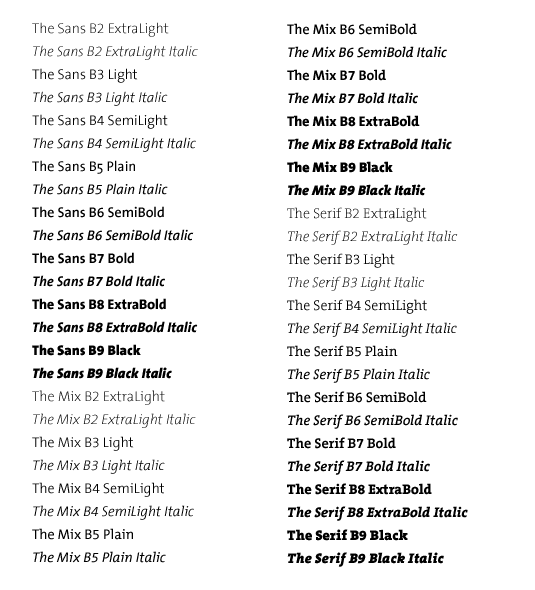
Unterschied Condensed und Narrow
gibt es eigentlich einen allgemeinen Unterschied zwischen Narrow und Condensed, oder nur bei den jeweiligen Familien? Manchmal ist die Narrow breiter und manchmal die Condensed. Eine Tendenz erkenne ich da niocht.
Ich schätze die beiden als synonym ein, vielleicht mit haarfeinen Unterschieden, wenn man sie im Helvetica(?)-Nummernsystem kategorisieren würde,
Hat das nicht was mit der Strichstärke zu tun? Condensed ist schmaler, behält aber die gleiche Strichstärke, während Narrow schmaler und dünner ist. Ich kann da komplett danebenliegen...
Das war auch meine erste Erinnerung, aber eine kurze Googlelei zeigte mir da keine Gewohnheitsbezeichnungen. Es ist echt schade, dass sich das System mit den zwei Achsen von Frutiger (hab's nachgeschlagen 🙂 ) nicht durchgesetzt hat.
@ThierryM hat das mal gut zusammengefasst:
noch einmal ausführlich: bei beiden schriften gibt die erste ziffer die strichstärke an.
frutiger
4 = light · 5 = roman · 6 = bold · 7 = black · 8 = extrablack · 9 = ultrablack
helvetica
2 = ultra light · 3 = thin · 4 = light · 5 = roman · 6 = medium · 7 = bold · 8 = heavy · 9 = black · 10 = extra black
bis hierhin finde ich das system nachvollziehbar. die zweite ziffer benennt nun eine weitere eigenschaft:
frutiger
5 = regular · 6 = italic · 7 = condensed
helvetica
3 = extended · 5 = regular · 6 = oblique · 7 = condensed
das heißt, du kannst jetzt – soweit die entsprechenden schnitte existieren – nummern kombinieren. die frutiger 46 ist die frutiger light italic, die frutiger 87 ist die frutiger extrablack condensed. die helvetica 33 ist die helvetica thin extended, die helvetica 77 ist die helvetica bold condensed. die klassifikation versagt allerdings, wenn – sagen wir mal – die helvetica extended oblique, die es tatsächlich gibt, damit beschrieben werden soll, da kursiv und extended über dieselbe ziffernposition bezeichnet werden. man müsste also regular/kursiv alleine auf die zweite ebene stellen und für die schriftweite eine dritte ziffer anhängen. da diese systeme ohnehin nicht mehr sonderlich verbreitet sind, wird das vermutlich kein mensch mehr weiterentwickeln, sondern auf die nummerierung verzichten oder dieses »problem« eben akzeptieren.
eine neuere schrift, die ein vergleichbares system verwendet, allerdings nur mit einer ziffer, ist die thesis basic von luc(as) de groot:
Vielleicht kann ja jemand, der eine der entsprechenden Schriften besitzt, dazu auch bei uns einen Wiki-Eintrag machen, in dem das System auch mit den Achsen demonstriert wird? Hier gibt es zudem auch Vorarbeiten mit handschriftlichen Anmerken zum System der Univers: https://www.eguide.ch/de/objekt/univers/
In rudimentärer Form findet sich das Frutigersche System auch bei den Google Fonts wieder (bezeichnet werden lediglich die „Gewichte“ der Schriftschnitte, kursive Schnitte werden als italic ergänzt, also „Thin 100 italic“, Condensed, Expanded etc. wird als Einzelfamilie behandelt, also z. B. condensed Schnitte von Encode Sans sind dann „Encode Sans Condensed“ etc.)
Thin 100
Extra Light 200
Light 300
Regular 400
Medium 500
Semi-Bold 600
Bold 700
Extra-Bold 800
Black 900